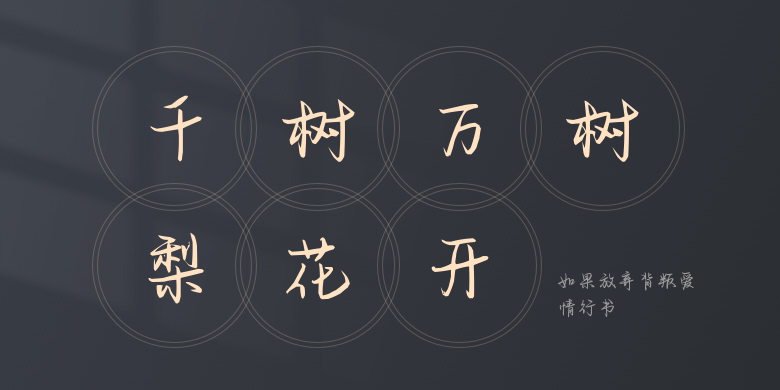
如果放弃背叛爱情行书
如果放弃背叛爱情行书,这款字体结构工整、笔画清晰,兼顾美观与易读性,适用于标题、正文、海报、包装、LOGO 等多种场景。字形优雅稳定,风格百搭耐看,适配日常排版与创意设计,让文字呈现更舒适、更具质感。如果放弃背叛爱情行书一笔一画,皆是细节,以均衡的比例、流畅的线条打造舒适视觉体验,字形端正大气,风格简约现代。无论是商业设计、品牌宣传还是日常排版,都能轻松驾驭,让文字更有格调与力量。如果放弃背叛爱情行书字体下载。